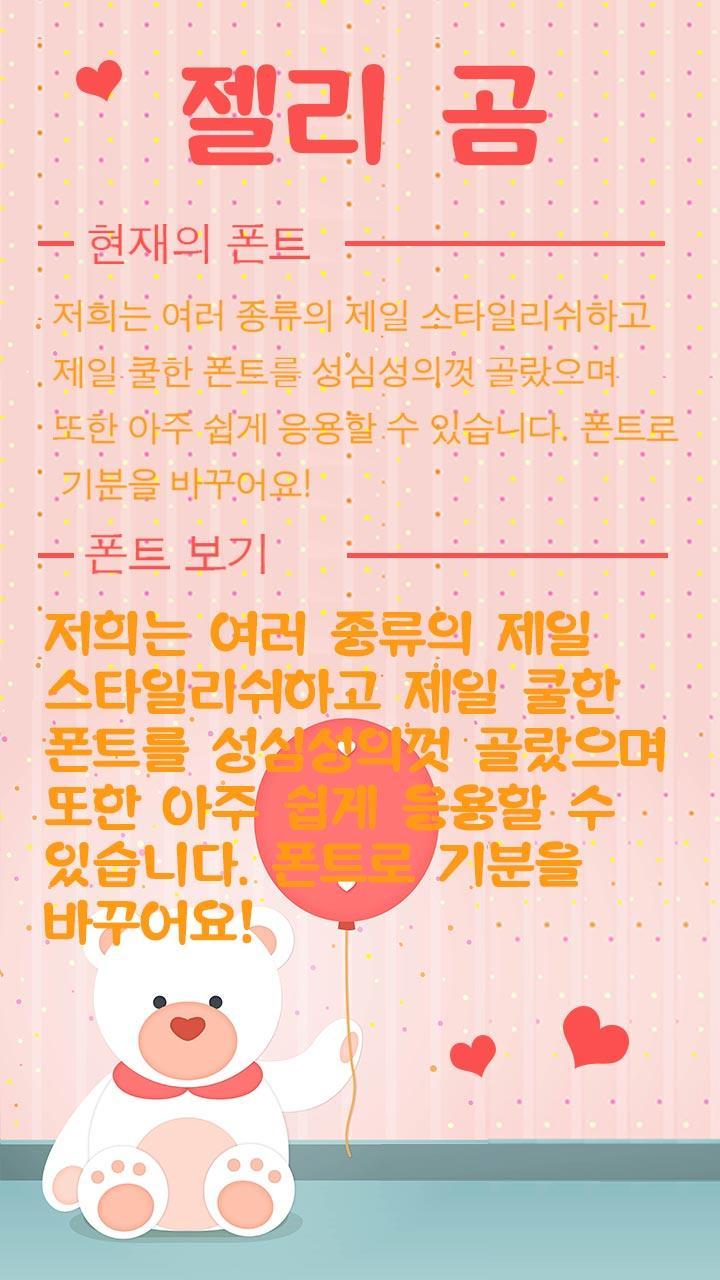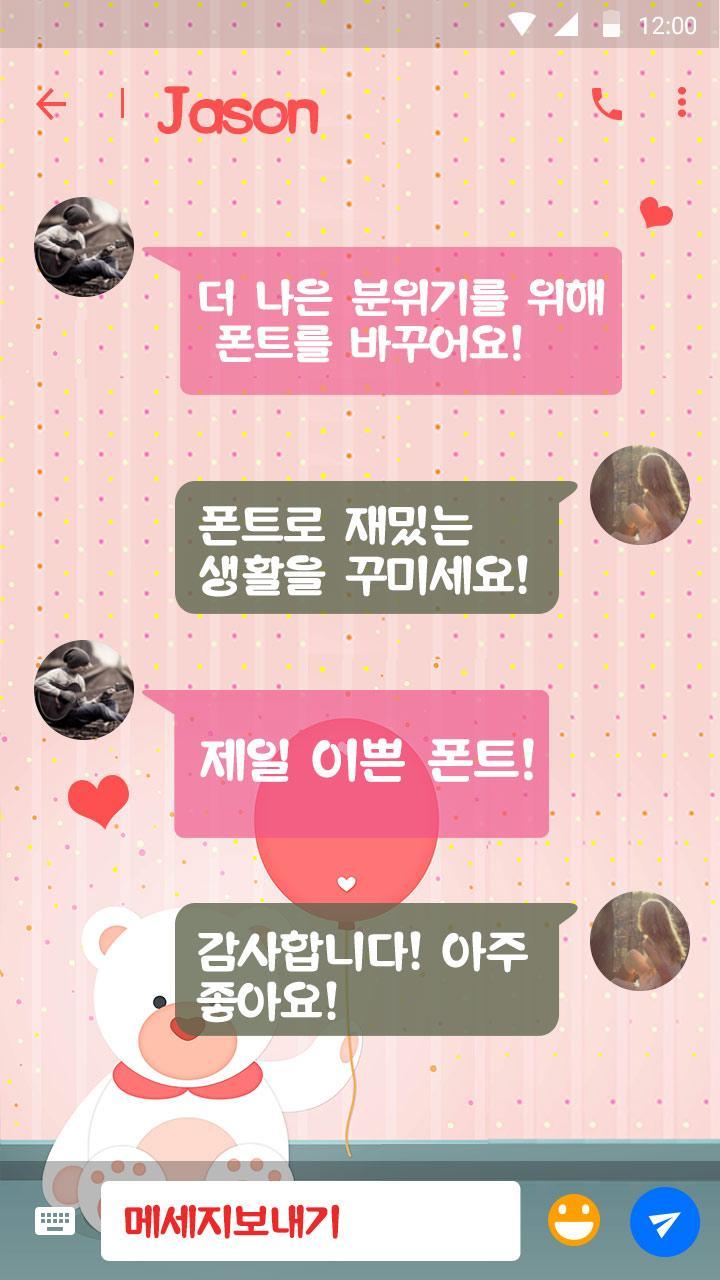
About FlipFont를 위한 젤리 곰 폰트
گمی بیئر کسی کو بھی اپنے فون یا ٹیبلٹ پر سسٹم فونٹ تبدیل کرنے کی اجازت دیتا ہے۔ یہ فونٹ میں مکمل تبدیلیوں یا جڑوں تک رسائی کے ل Fl فلپ فونٹ ™ (سیمسنگ گلیکسی ایس 3 ، ایس 4 ، ایس 5 ، نوٹ ، نوٹ II ، نوٹ III) والے آلات پر معاون ہے۔ یہ بالکل اینڈروئیڈ کے لئے بہترین انسٹالر فلپ فانٹ ہے!
آپ اپنے آلے کے فونٹ کو فونٹ پیک برائے اینڈروئیڈ فلپ فانٹ کے ساتھ مفت تبدیل کرسکتے ہیں۔ سیمسنگ گلیکسی پر نصب پلٹ فانٹ فونٹ چینجر پروگرام کا استعمال جب آپ فلپ فونٹ براؤز کرتے ہیں تو ، بنڈل شدہ فونٹ ایکسپلورر ظاہر ہوتا ہے۔ آپ کو اپنے ذائقہ کے مطابق حیرت انگیز اور کامل فونٹ اسٹائل ملیں گے۔ فون کے پورے فونٹ کو گمی بیئر میں تبدیل کریں۔ کسٹم فونٹ استعمال کریں ، گمی بیئر کی خصوصیت ہم آہنگ ہے۔ اب آپ کو اپنے فون کا تعی beن ہونا پڑے گا۔ اور آپ دوسرے فونٹس جیسے گمی بیئر کو Hifont ایپ کے ذریعے تلاش کرسکتے ہیں۔